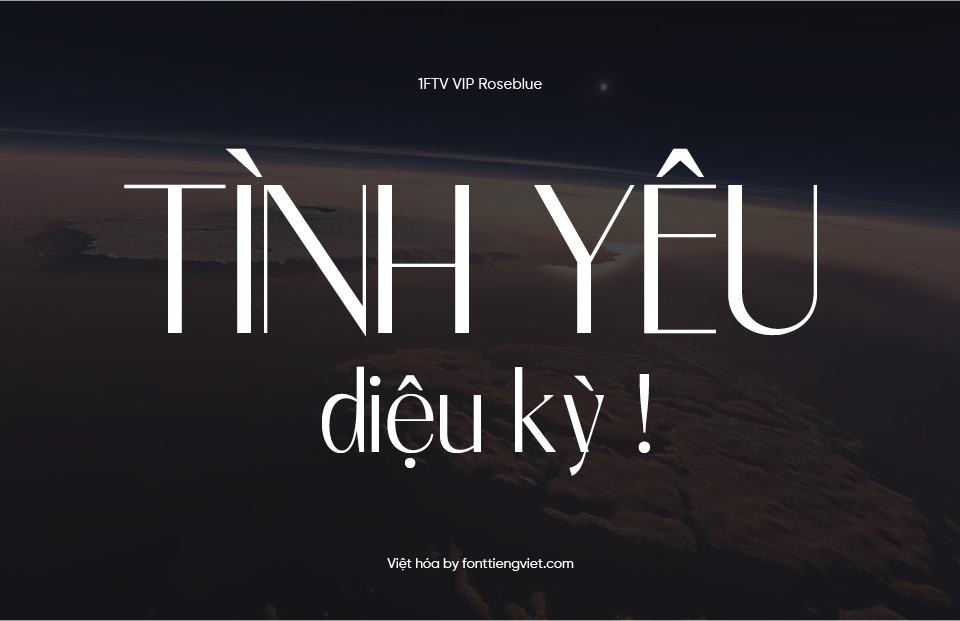
Font việt hóa 1FTV VIP Roseblue – Bộ font chữ nghệ thuật cực đẹp cho thiết kế chuyên nghiệpGiới thiệu về bộ Font việt hóa 1FTV VIP Roseblue trong thiết kế đồ họaTrong thế giới sáng tạo ngày nay, việc lựa chọn một Font Miễn Phí phù hợp đóng vai trò quyết định đến sự thành công của một bản thiết kế. Font việt hóa 1FTV VIP Roseblue nổi lên như một hiện tượng nhờ sự kết hợp hoàn hảo giữa nét hiện đại và phong cách cổ điển lãng mạn. Đây là một bộ phông chữ được tinh chỉnh kỹ lưỡng về dấu tiếng Việt, giúp các nhà thiết kế tại Việt Nam giải quyết triệt để lỗi hiển thị ký tự khi làm việc trên các phần mềm như Adobe Photoshop, Illustrator hay Canva. Sự thanh thoát trong từng nét chữ của Roseblue mang lại cảm giác nhẹ nhàng, sang trọng, đặc biệt phù hợp cho các dự án đòi hỏi tính thẩm mỹ cao và sự tỉ mỉ trong chi tiết.Những đặc điểm nổi bật của Font việt hóa 1FTV VIP RosebluePhong cách thiết kế bay bổng và linh hoạtFont việt hóa 1FTV VIP Roseblue sở hữu các đường nét thanh mảnh nhưng vô cùng chắc chắn. Cấu trúc của bộ font này được xây dựng dựa trên sự cân bằng giữa các khoảng trắng, tạo nên một tổng thể hài hòa và dễ nhìn. Điểm đặc biệt của Roseblue chính là các ký tự thay thế (alternates) và các nét uốn lượn (swashes) đi kèm, giúp người dùng có thể tùy biến dòng văn bản theo ý thích cá nhân. Đối với các bạn học sinh, sinh viên hoặc những người mới bắt đầu học thiết kế, đây là công cụ đắc lực để tạo ra những sản phẩm chuyên nghiệp mà không mất quá nhiều công sức căn chỉnh thủ công.Tương thích đa nền tảng và dễ dàng cài đặtMột ưu điểm không thể bỏ qua của Font việt hóa 1FTV VIP Roseblue là khả năng tương thích tuyệt vời trên cả hệ điều hành Windows và macOS. Sau khi tải về, bạn chỉ cần vài thao tác chuột đơn giản là đã có thể sử dụng ngay trong các trình soạn thảo văn bản như Word hoặc các công cụ thiết kế chuyên sâu. Bộ font này không chỉ hỗ trợ tốt cho việc in ấn trên thiệp cưới, menu nhà hàng hay bìa sách mà còn hiển thị rất sắc nét trên các nền tảng kỹ thuật số như bài đăng mạng xã hội, tiêu đề website hay slide thuyết trình trong môi trường học đường.Ứng dụng thực tế của Font việt hóa 1FTV VIP RoseblueSáng tạo nội dung trên mạng xã hội và truyền thôngVới sự phát triển của nội dung hình ảnh, Font việt hóa 1FTV VIP Roseblue thường xuyên được các bạn trẻ sử dụng để làm Quotes, viết lời tựa cho các video ngắn trên TikTok hoặc Instagram. Màu sắc của font chữ khi kết hợp với các tông màu pastel hoặc trắng đen sẽ tạo nên một phong cách đậm chất nghệ thuật. Ngoài ra, trong giáo dục, các thầy cô giáo cũng có thể dùng bộ font này để trang trí bảng tin, làm bằng khen hoặc tài liệu giảng dạy sinh động hơn, giúp học sinh hứng thú hơn với bài học qua những giao diện trình bày bắt mắt và chuyên nghiệp.Lời kết và hướng dẫn tải Font việt hóa 1FTV VIP RoseblueTổng kết lại, Font việt hóa 1FTV VIP Roseblue là một lựa chọn không thể thiếu trong bộ sưu tập của bất kỳ ai yêu thích cái đẹp và sự tinh tế. Việc sở hữu một bộ font chữ đã được tối ưu hóa tiếng Việt hoàn toàn giúp bạn tiết kiệm thời gian và nâng cao chất lượng công việc một cách đáng kể. Đừng ngần ngại trải nghiệm ngay để thấy sự khác biệt mà nó mang lại cho dự án của bạn. Để tìm kiếm thêm nhiều tài nguyên hữu ích khác, hãy truy cập vào Font Miễn Phí, Font Việt Hóa, Font việt hóa 1FTV VIP Roseblue để tải về và cập nhật những xu hướng thiết kế mới nhất hoàn toàn miễn phí ngay hôm nay.
Font việt hóa 1FTV VIP Roseblue